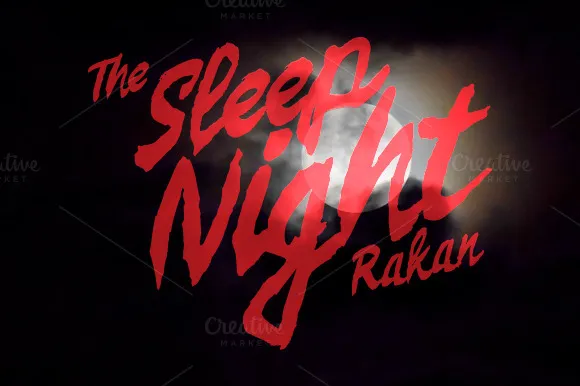
Tree Shoots Brush Font – Download Grátis
A Tree Shoots Brush Font é a escolha perfeita para quem busca dar vida às criações digitais com uma mão-dura personalidade. Com seus traços artesanais e delicados, essa fonte de brush está sempre à procura de trazer destaque aos trabalhos. Ideal tanto para logomarcas quanto sites, cartões de convite e até mesmo embalagens, a Tree Shoots Brush Font é uma adição imediata e incrivelmente bonita ao seu portfólio gráfico. Com sua elegância natural e aparente habilidade manual, essa font se destaca em um amplo espectro de projetos, desde cartões de visita até revistas e materiais de embalagem. Seja onde você lhe mandar esse convite para o seu próximo evento ou na hora de criar uma marca forte que irá impressionar seus clientes, Tree Shoots Brush Font é uma opção de qualidade inegável para qualquer designer gráfico.